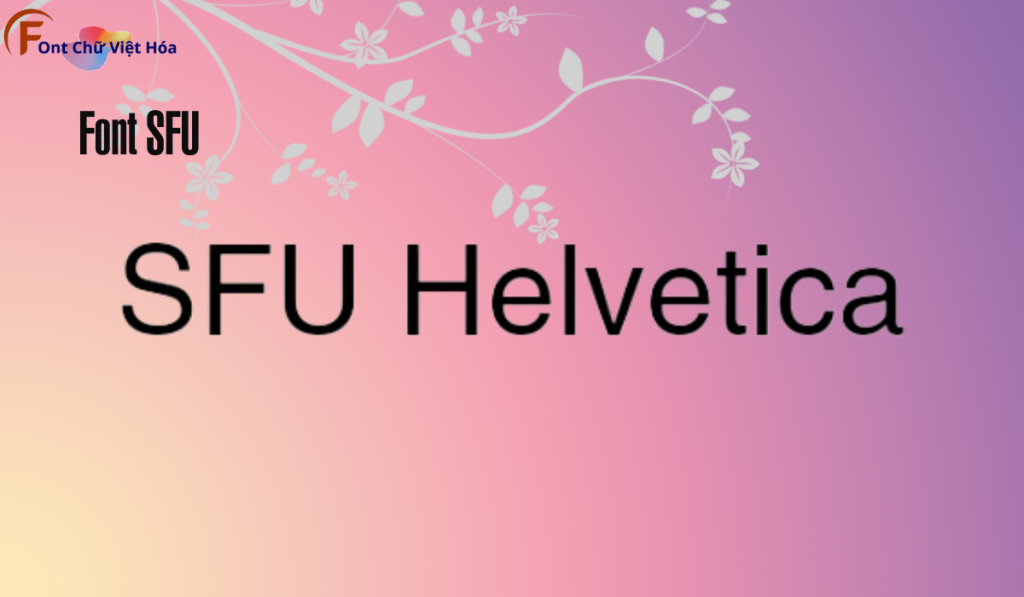
Font SFU Helvetica Việt Hóa
Tác giả: Helvetica
Phân loại: Hiện đại, Chuyên nghiệp
Kiểu chữ: Sans-serif
Độ dày: Light, Regular, Medium, Bold
SFU Helvetica Việt Hóa, thuộc bộ font SFU, là biểu tượng của sự thanh thoát và tinh tế với phong cách sans-serif hiện đại. Font này được thiết kế nhằm mục tiêu tạo ra sự rõ ràng và dễ đọc, đặc biệt phù hợp cho các thiết kế như poster, logo, và tiêu đề. Đặc điểm hình dạng của SFU Helvetica là các đường nét sắc sảo và tỷ lệ chữ cân đối, giúp tối ưu hóa không gian và tạo ấn tượng thị giác mạnh mẽ. Font này cũng đã được Việt hóa, mang đến sự linh hoạt và tiện dụng cho các dự án thiết kế bằng tiếng Việt, giúp người dùng dễ dàng tiếp cận và sử dụng.